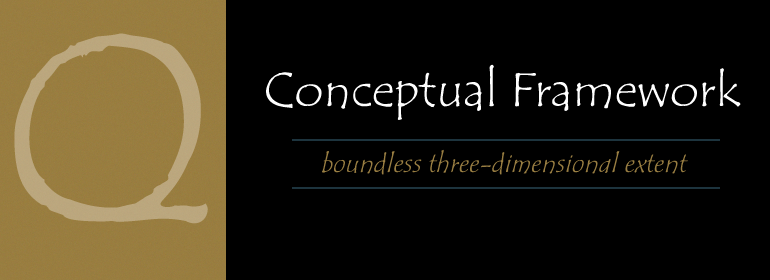
ITC Tempus® Sans
字体品牌: ITC(Monotype) 设计师:Grimshaw,Phill 字体分类:衬线体 字体属性:外文 字符集:Unicode 发布时间: 2018
ITC Tempus是英国设计师Phill Grimshaw的作品。他声称每个书法家的愿望都是用钢笔画出完美的罗马大写字母,但是他承认这非常困难。对于这种字体,Grimshaw在便宜的多孔纸上使用了自来水钢笔,当然墨水会洇。由此而形成的格式很经典,但其粗糙的边缘与罗马式的完美外观有所不同。而且,Tempus Sans只是去掉衬线的Tempus,但字符的比例仍然很好。” Grimshaw说。由于其粗糙的特征,字体在较大尺寸显示时效果最佳,但即使在较小的尺寸下也能保持其字符清晰。”
ITC Tempus is the work of British designer Phill Grimshaw. He claims that every calligrapher's aspiration is to draw perfect roman capitals with a pen, but admits that this is extremely difficult. For this typeface, Grimshaw used a fountain pen on cheap, porous paper and, of course, the ink bled. The resulting forms are classic but their rugged edges deviate from the perfection of roman type. And Tempus Sans is just Tempus with the serif surgically removed, yet the proportions of the characters work nicely," says Grimshaw. Because of its rough quality, the typeface works best in larger point sizes, yet maintains its characters even in smaller sizes."